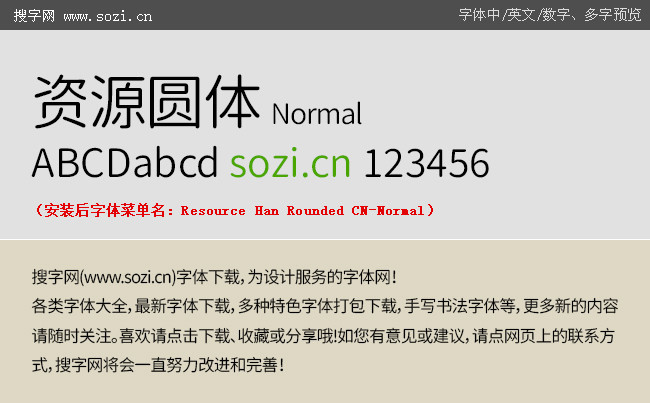
資源圓體Normal
搜字網(wǎng)給大家提供一款資源圓體Normal中文字體下載,資源圓體是一款基于思源黑體改造而成的免費(fèi)可商用圓體字體。除了資源圓體還有源柔黑體(也稱思源柔黑,由日本設(shè)計師改造,對日文支持較好)和源泉圓體(由臺灣設(shè)計師改造,對繁體支持較好)也都是基于思源黑體改造而成的免費(fèi)圓體字體。相對于源柔黑體和源泉圓體,資源圓體則對簡體字體支持較好,因?yàn)樗怯蓢鴥?nèi)設(shè)計師Cyano Hao基于中國版的思源黑體改造而成的圓體字體。